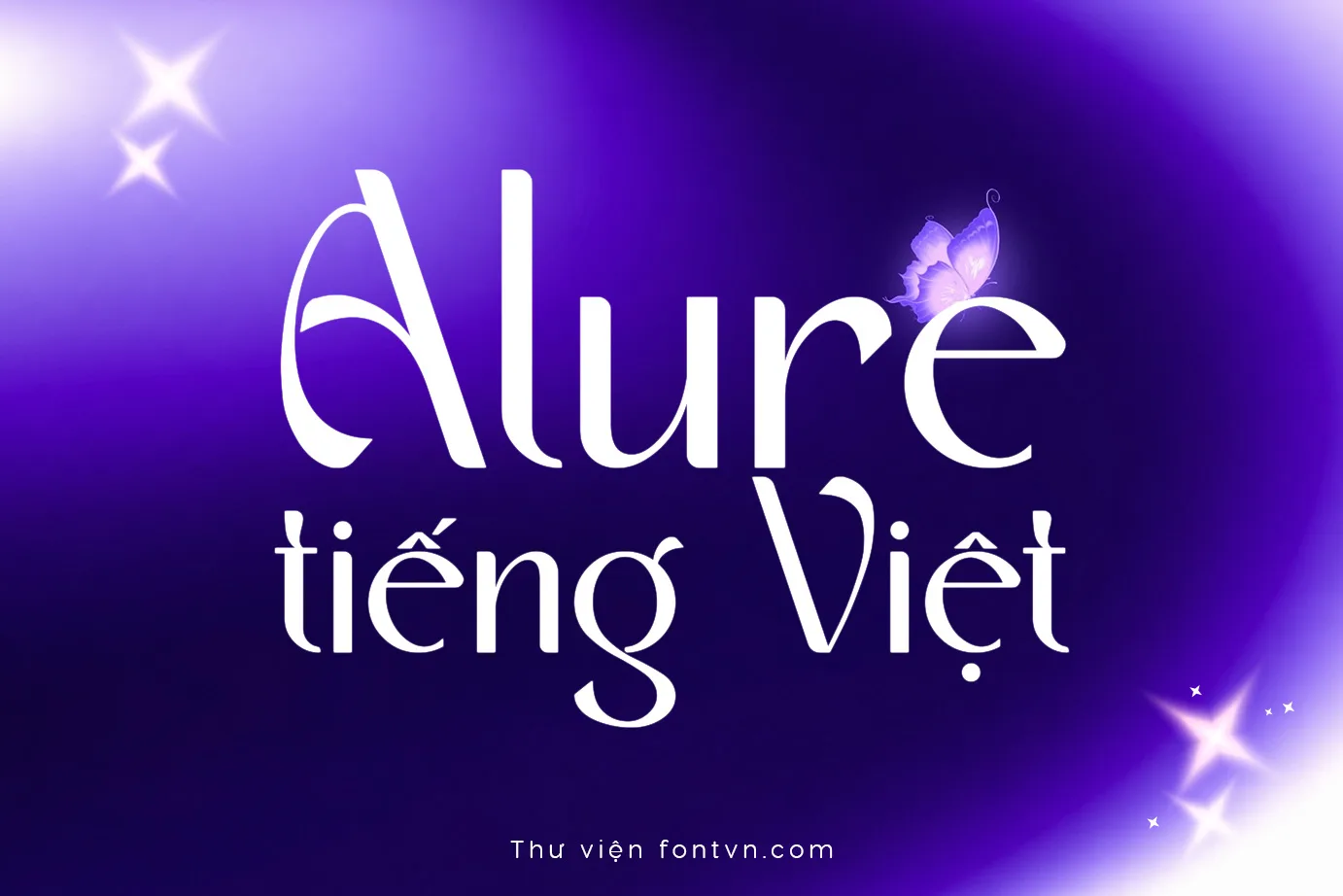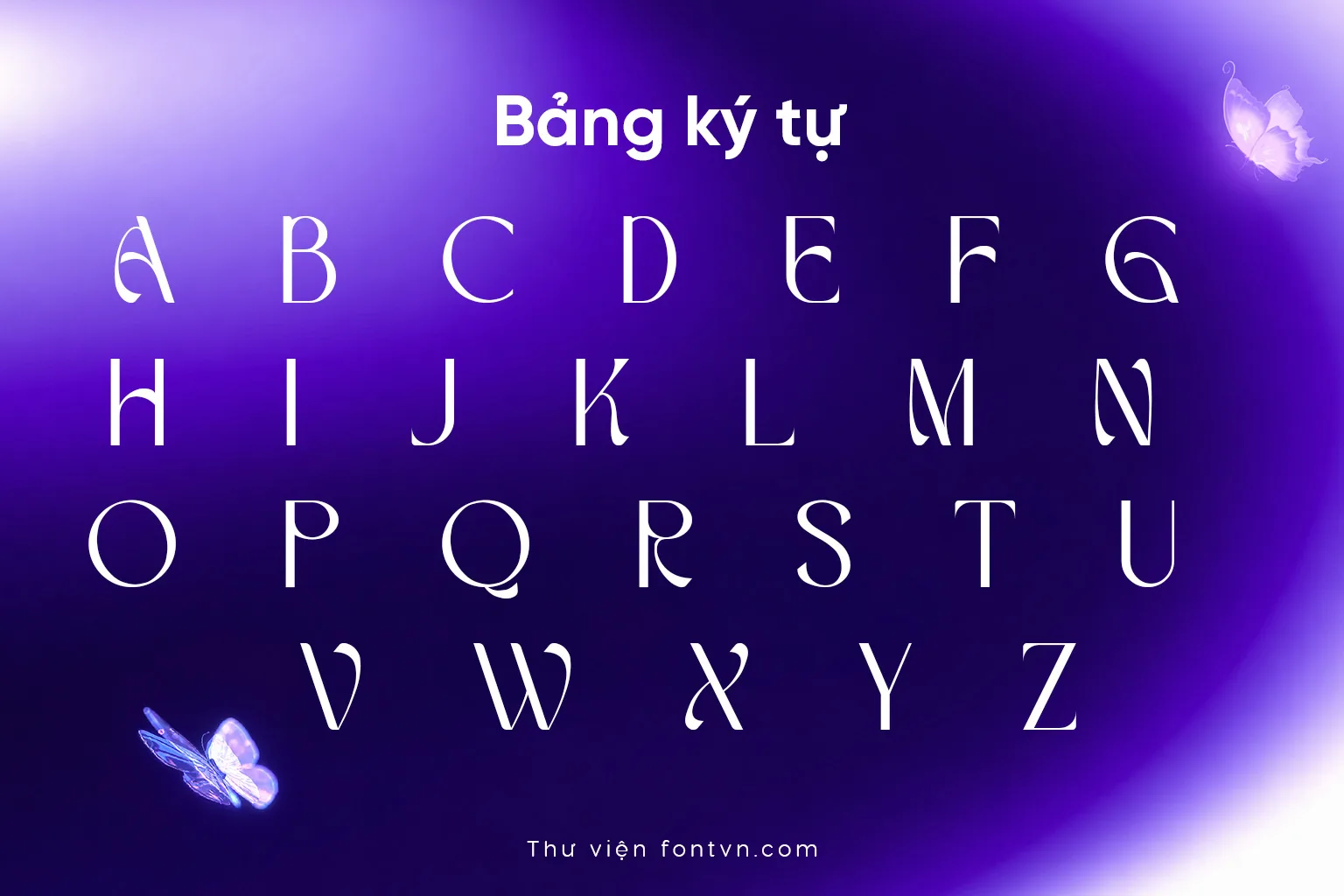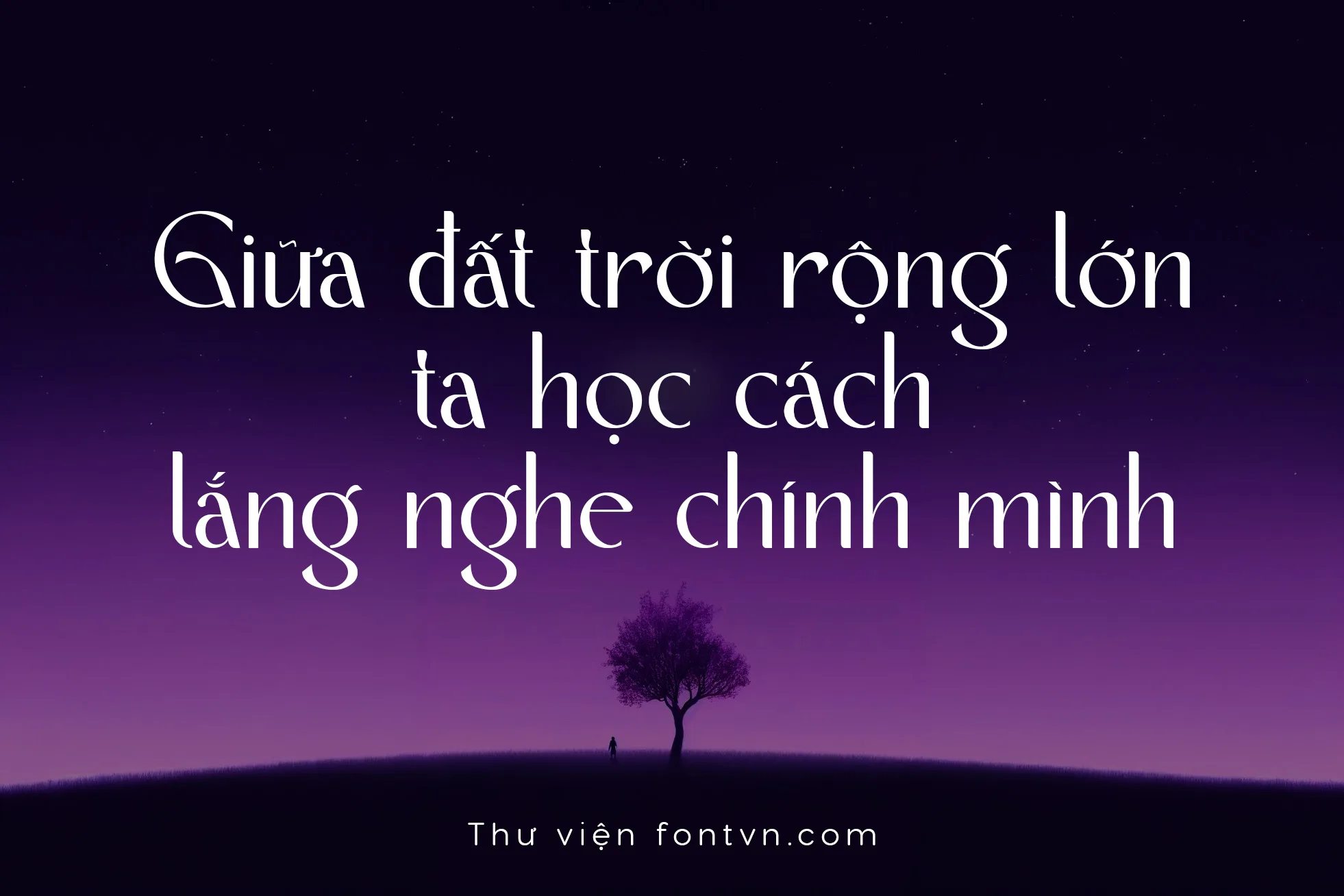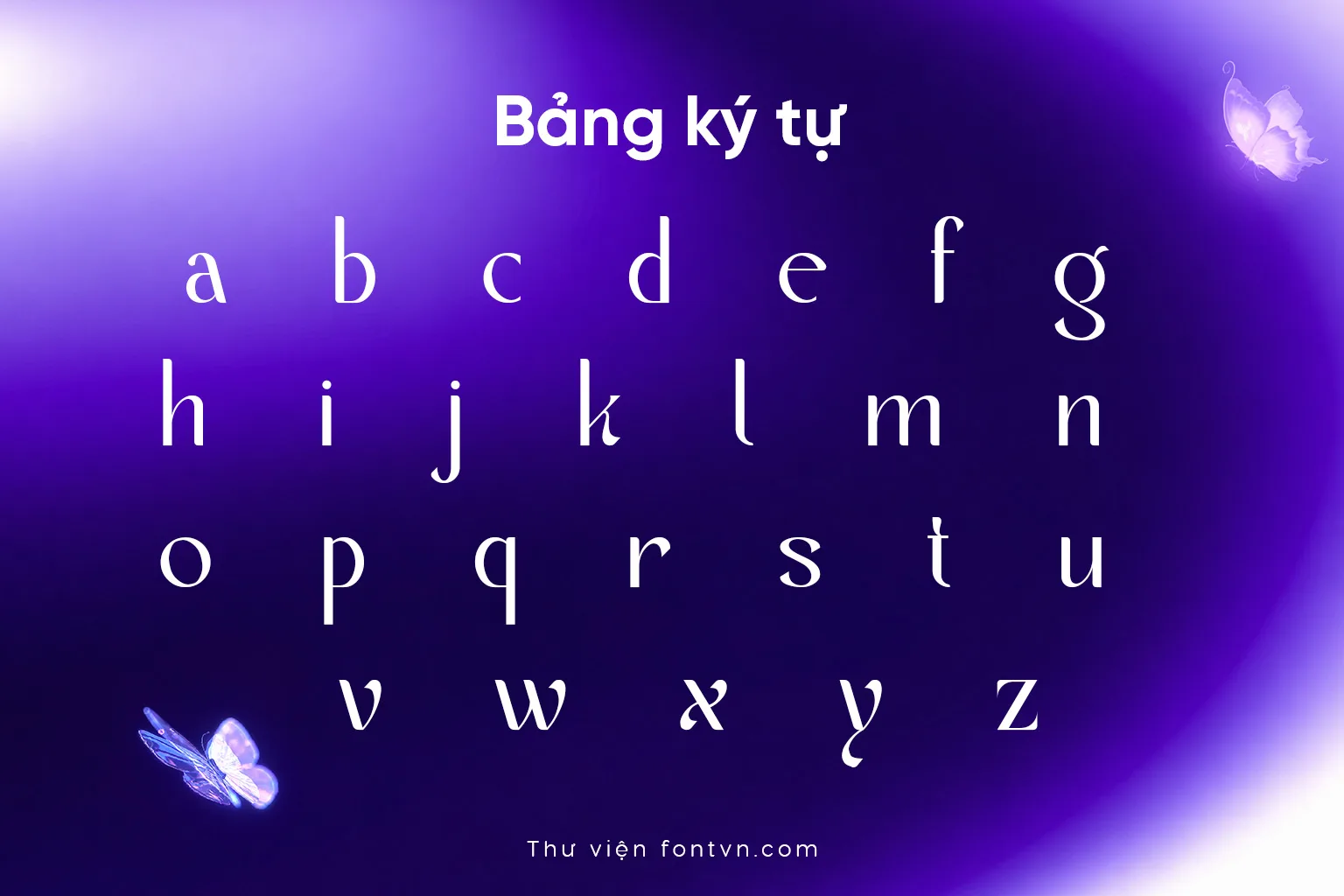
DVN Alure tiếng Việt – Typeface thanh lịch mang tinh thần hiện đại
DVN Alure là một kiểu chữ serif mang phong cách thanh lịch và thời trang, nổi bật với sự tương phản mạnh giữa nét thanh và nét đậm, những đường cong mềm mại cùng các chi tiết chữ mang tính biểu cảm cao. Font tạo cảm giác sang trọng, tinh tế nhưng vẫn có cá tính riêng, đặc biệt phù hợp với thiết kế editorial, thời trang, beauty, branding, poster và tiêu đề nổi bật.
Điểm đáng chú ý của DVN Alure là hệ thống ký tự hỗ trợ tiếng Việt, được xử lý đồng bộ với phong cách chữ Latin, giúp các dấu tiếng Việt hòa nhập tự nhiên vào tổng thể thiết kế thay vì trở thành những chi tiết rời rạc.